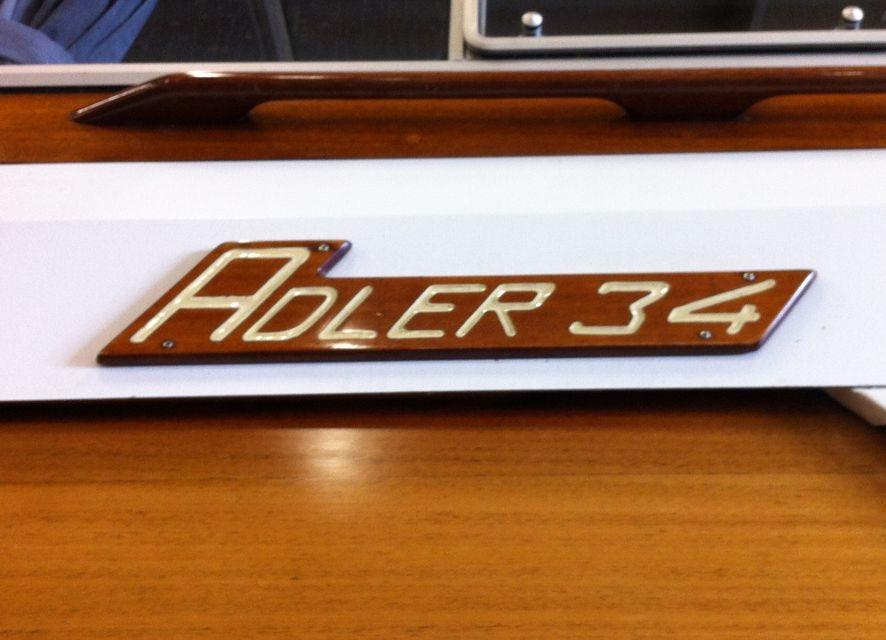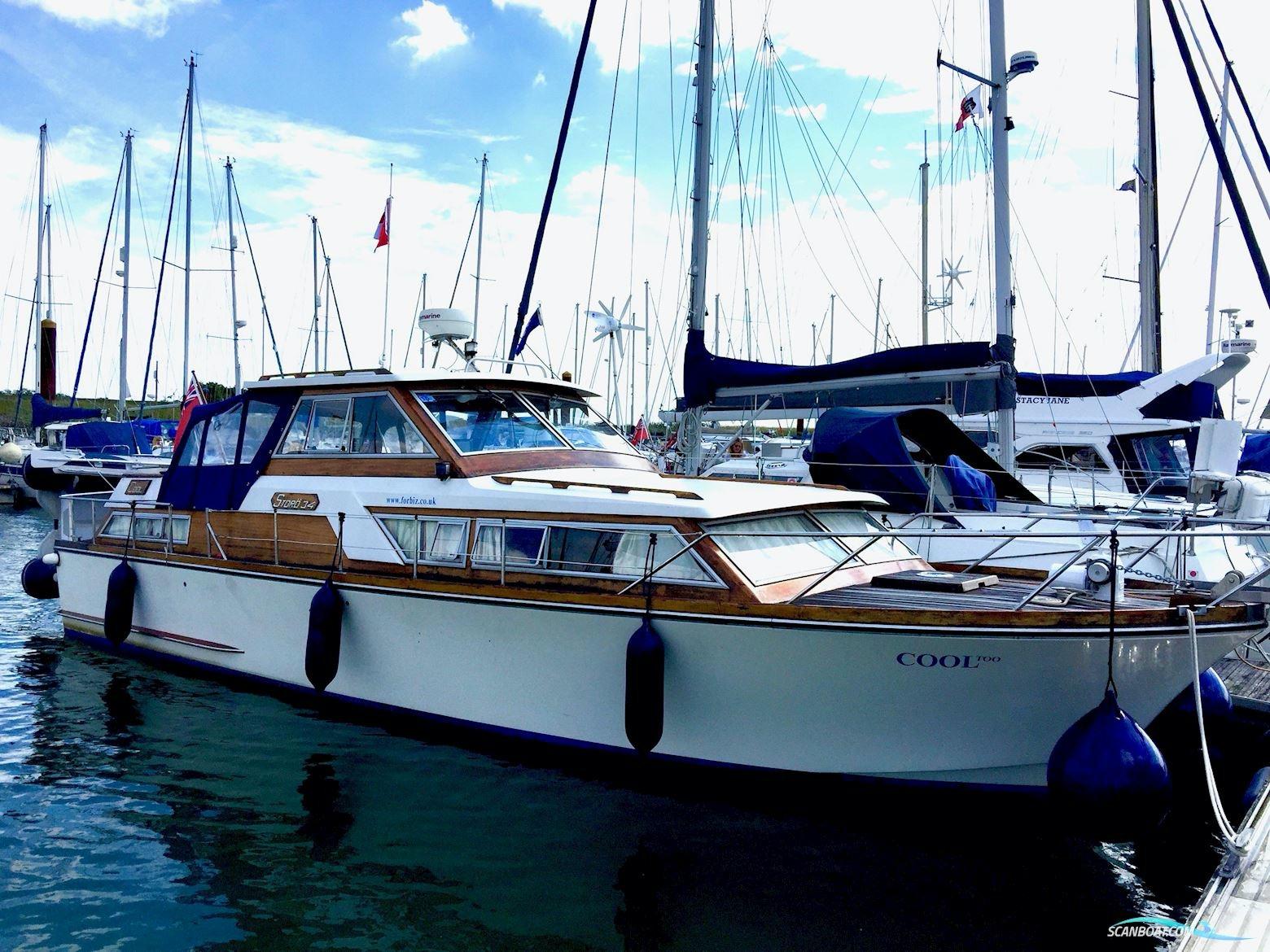
Störo 34 / Adler 34
Ich suche eine Schrift von einem Oldtimer Boot. Mit What the Font habe ich schon versucht, die Schriftart herauszubekommen leider vergeblich. Vielleicht könnt ihr mir ja hier helfen...
Adler 34 sieht nicht nach einem regulären Computer-Outline-Font aus. Das ist entlang einer Skelettlinie graviert. Ließe sich von einer guten frontalen Aufnahme aber leicht nachempfinden.
COOL ist sicherlich ein Computer-Font, aber die Abbildung ist nicht detailliert und die Buchstaben nicht spezifisch genug.
Ich denke auch, dass hier Schablonen zugrundeliegen oder eine selbst erstellte Vorlage mit dem Pantographen und der Oberfräse übertragen wurde. Die Buchstabenformen und Neigung unterscheiden sich ja von Jahr zu Jahr, wenn man sich die alten Kataloge anschaut …